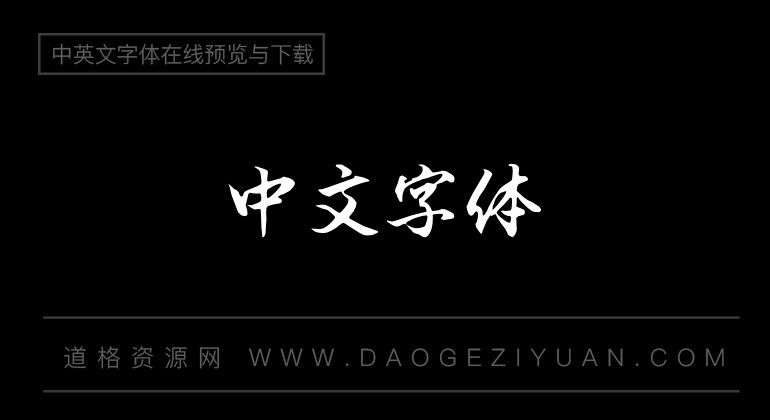
A-OTF 角新行書 Std M
A-OTF 角新行書 Std M 是一款日本传统行书字体,由日本字体设计师高桥英明设计,它采用自动开放式字型格式(A-OTF),具有良好的可读性和可视性。它的特点是细节丰富,并且采用细节丰富的笔画,使字体更加精细和精致。它的字形大小和角度也可以通过软件调整,使文字更加清晰,更加美观。它可以用于日常文字排版,也可用于报纸、杂志、书籍等出版物的排版。
A-OTF 角新行書 Std M是一款非常不错的手写艺术字体,具有很好的视觉感,适合于文化类的宣传设计、商业类品牌的广告和产品包装设计以及个性化文字排版等较多场景。